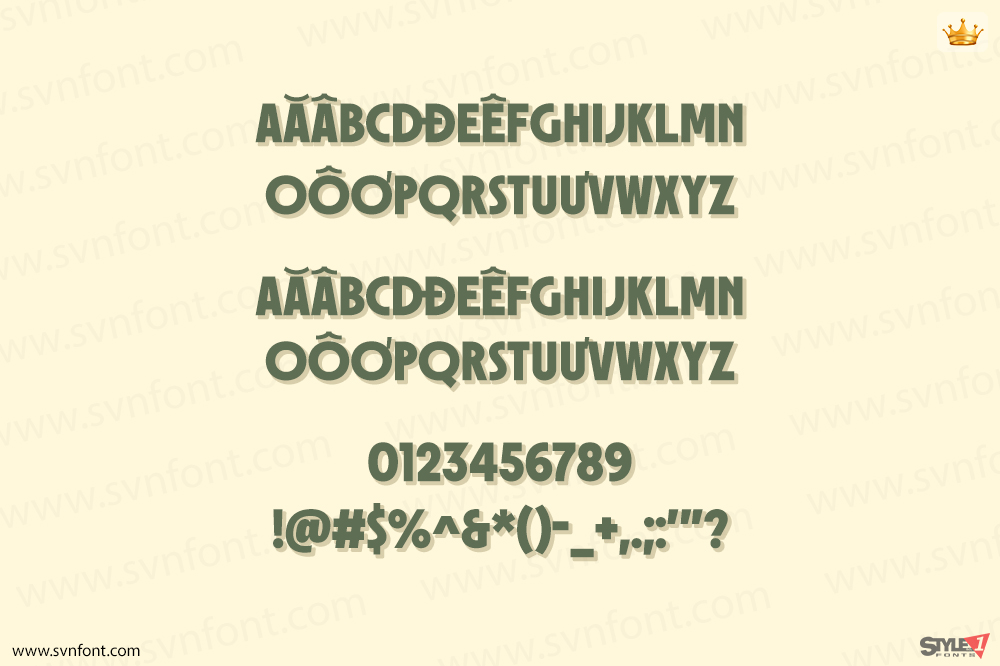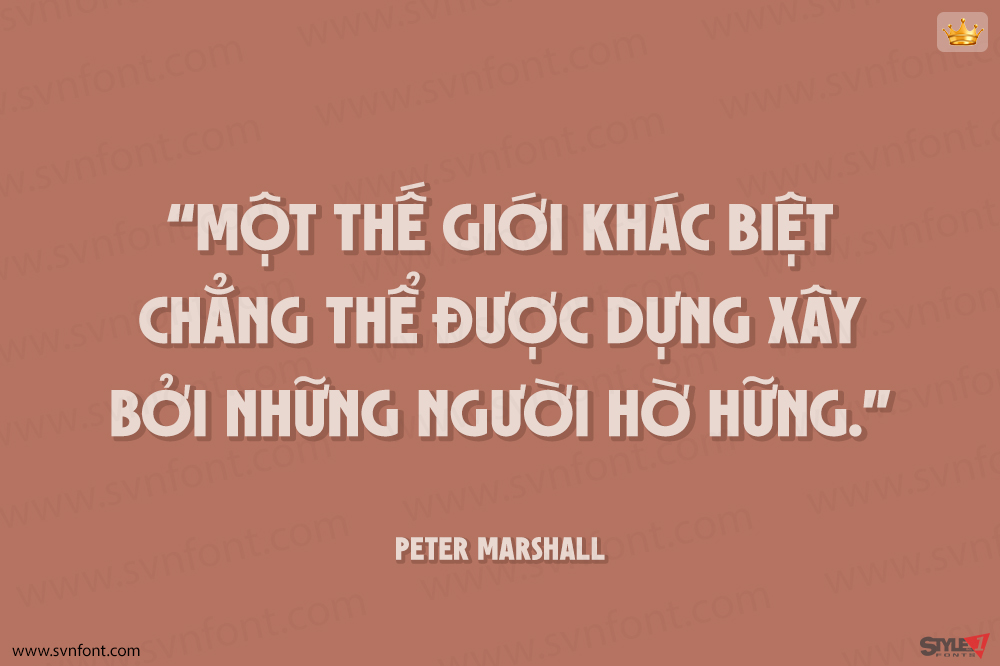
Xin giới thiệu sự bổ sung hoàn hảo cho thiết kế của bạn! Phông chữ mạnh mẽ và nam tính! Bosten được thiết kế đặc biệt để tạo ra tác động mạnh mẽ, cho dù bạn đang tạo tiêu đề hay xây dựng thông điệp thương hiệu. Với những đường nét bóng bẩy và mạnh mẽ, phông chữ này chắc chắn sẽ thu hút sự chú ý của khán giả và để lại ấn tượng lâu dài.
Cho dù bạn đang tạo tài liệu marketing, thiết kế trang web, thiết kế logo, bao bì, quảng cáo, quần áo, hàng hóa, v.v., Bosten là lựa chọn hoàn hảo. Vậy còn chần chừ gì nữa? Hãy đưa thương hiệu của bạn lên một tầm cao mới với phông chữ mạnh mẽ này ngay hôm nay!
Nhà thiết kế: Annas Alam Yahya
Nhà phát hành: Letteralle